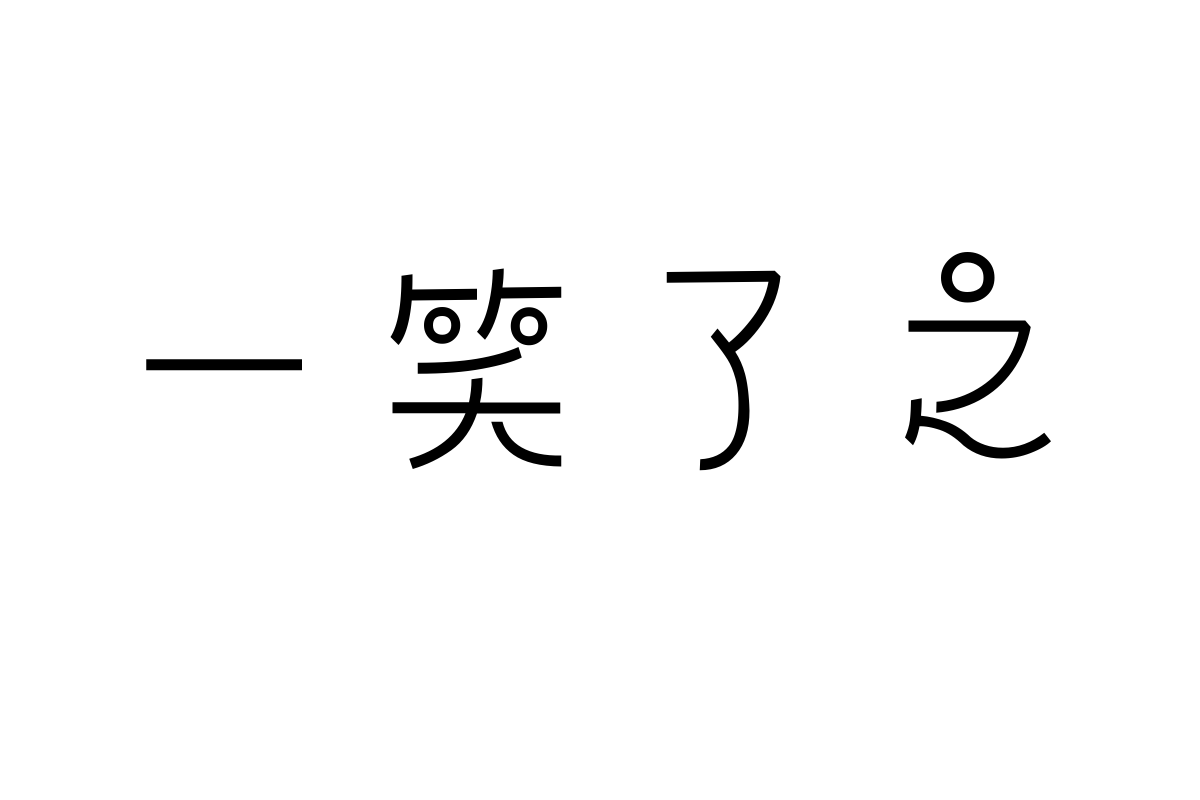
三极气泡体是一种字体设计,它的特点是在每个字母的中间都有一个小的气泡。这种字体的设计灵感来自于海洋中的气泡,给人一种清新、自然的感觉。
这种字体的特点是简洁明了,易于阅读,适合用于标题、广告等需要突出显示的部分。同时,由于其独特的设计,也使得这种字体具有一定的艺术感和视觉冲击力。
总的来说,三极气泡体是一种非常实用且具有艺术性的字体,适合用于各种需要突出显示文字的场合。